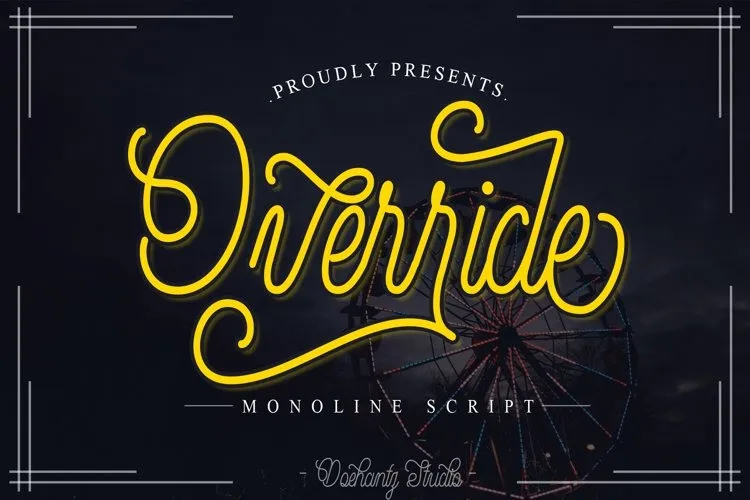
A Override é uma fonte script monoline que transmite movimento natural e elegância ideal para assinaturas. Ela foi criada pelo Doehantz Studio e está disponível para download pela plataforma de competição 99designs. Esta fonte não apenas oferece um estilo único, mas também possui diversas alternativas para caracteres, tornando-a perfeita para combinar em projetos de design. Com sua beleza singular e variedade, a Override se destaca como uma escolha excepcional para quem busca uma fonte script que brilhe tanto no papel quanto online. Esta font é especialmente adequada para trabalhos que exigem elegância e sofisticação, sem deixar de oferecer uma personalidade única ao seu projeto.